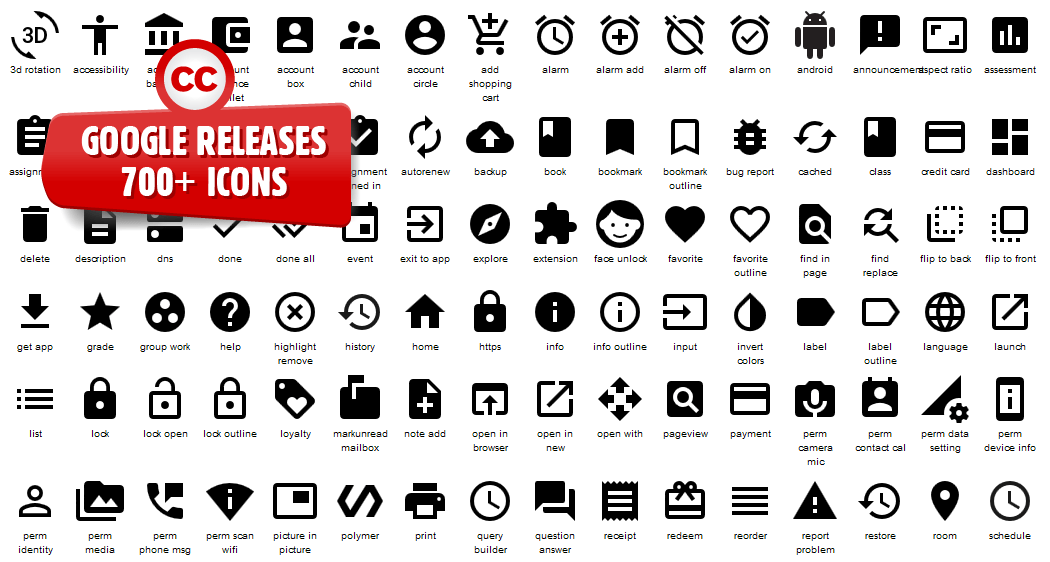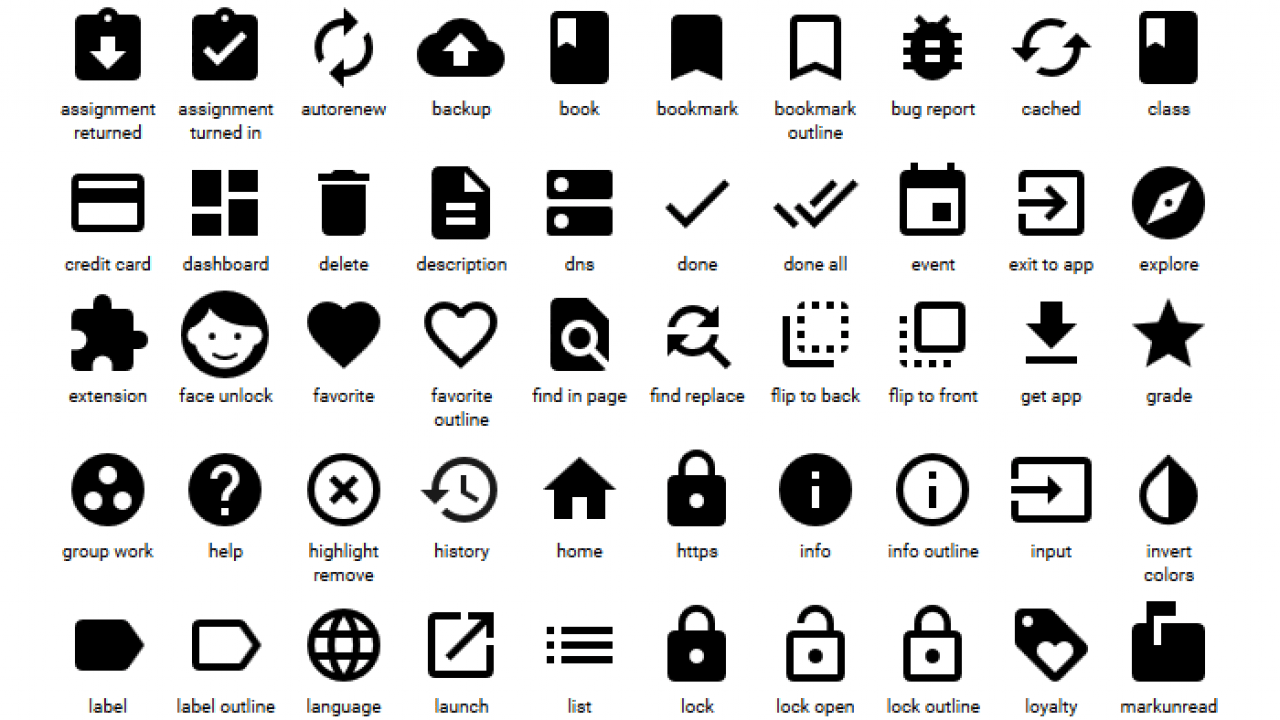
Google Font Icon . Material icons(マテリアルアイコン)は、 googleが提供するオープンソースのアイコンフォントサービス で、様々な種類、スタイルのアイコンを無料で利用することができます。 以前. Google fontsでは “material icons”という、マテリアルデザインに合わせて作られたアイコンフォントも 用意されています。 人によって「google fonts icons」や「google material icons」. Making the web more beautiful, fast, and open through great typography Material symbols are our newest icons consolidating over 2,500 glyphs in a single font file with a wide range of design variants. Material icons is an icon font useful for implementing google's material design language. (2022年現在、googleは、material symbolsとmaterial iconsの2つのアイコンフォントを提供しています。 この記事では、 material symbols の特徴や基本的な使い方、使用例を紹介. Google fonts (グーグルフォント)にマテリアルアイコンが登場しました。 google fonts iconsのサイトはこちら.
Material symbols are our newest icons consolidating over 2,500 glyphs in a single font file with a wide range of design variants. Google fontsでは “material icons”という、マテリアルデザインに合わせて作られたアイコンフォントも 用意されています。 人によって「google fonts icons」や「google material icons」. Google fonts (グーグルフォント)にマテリアルアイコンが登場しました。 google fonts iconsのサイトはこちら. Material icons is an icon font useful for implementing google's material design language. Material icons(マテリアルアイコン)は、 googleが提供するオープンソースのアイコンフォントサービス で、様々な種類、スタイルのアイコンを無料で利用することができます。 以前. (2022年現在、googleは、material symbolsとmaterial iconsの2つのアイコンフォントを提供しています。 この記事では、 material symbols の特徴や基本的な使い方、使用例を紹介. Making the web more beautiful, fast, and open through great typography
Google Font Icon Material icons(マテリアルアイコン)は、 googleが提供するオープンソースのアイコンフォントサービス で、様々な種類、スタイルのアイコンを無料で利用することができます。 以前. Material symbols are our newest icons consolidating over 2,500 glyphs in a single font file with a wide range of design variants. Google fontsでは “material icons”という、マテリアルデザインに合わせて作られたアイコンフォントも 用意されています。 人によって「google fonts icons」や「google material icons」. Material icons is an icon font useful for implementing google's material design language. Material icons(マテリアルアイコン)は、 googleが提供するオープンソースのアイコンフォントサービス で、様々な種類、スタイルのアイコンを無料で利用することができます。 以前. Google fonts (グーグルフォント)にマテリアルアイコンが登場しました。 google fonts iconsのサイトはこちら. Making the web more beautiful, fast, and open through great typography (2022年現在、googleは、material symbolsとmaterial iconsの2つのアイコンフォントを提供しています。 この記事では、 material symbols の特徴や基本的な使い方、使用例を紹介.
Google Font Icon Material icons(マテリアルアイコン)は、 googleが提供するオープンソースのアイコンフォントサービス で、様々な種類、スタイルのアイコンを無料で利用することができます。 以前. Making the web more beautiful, fast, and open through great typography Material symbols are our newest icons consolidating over 2,500 glyphs in a single font file with a wide range of design variants. Google fontsでは “material icons”という、マテリアルデザインに合わせて作られたアイコンフォントも 用意されています。 人によって「google fonts icons」や「google material icons」. (2022年現在、googleは、material symbolsとmaterial iconsの2つのアイコンフォントを提供しています。 この記事では、 material symbols の特徴や基本的な使い方、使用例を紹介. Material icons is an icon. Google Font Icon.
Google Font Icon Text Effect and Logo Design Font Google Font Icon Material icons is an icon font useful for implementing google's material design language. Material symbols are our newest icons consolidating over 2,500 glyphs in a single font file with a wide range of design variants. Making the web more beautiful, fast, and open through great typography (2022年現在、googleは、material symbolsとmaterial iconsの2つのアイコンフォントを提供しています。 この記事では、 material symbols の特徴や基本的な使い方、使用例を紹介. Google fonts (グーグルフォント)にマテリアルアイコンが登場しました。 google fonts iconsのサイトはこちら. Material. Google Font Icon.
Google Font Icon Material symbols are our newest icons consolidating over 2,500 glyphs in a single font file with a wide range of design variants. Google fonts (グーグルフォント)にマテリアルアイコンが登場しました。 google fonts iconsのサイトはこちら. Material icons(マテリアルアイコン)は、 googleが提供するオープンソースのアイコンフォントサービス で、様々な種類、スタイルのアイコンを無料で利用することができます。 以前. Making the web more beautiful, fast, and open through great typography Google fontsでは “material icons”という、マテリアルデザインに合わせて作られたアイコンフォントも 用意されています。 人によって「google fonts icons」や「google material icons」. Material icons is an icon font. Google Font Icon.
Google Font Icon Material symbols are our newest icons consolidating over 2,500 glyphs in a single font file with a wide range of design variants. Google fonts (グーグルフォント)にマテリアルアイコンが登場しました。 google fonts iconsのサイトはこちら. Google fontsでは “material icons”という、マテリアルデザインに合わせて作られたアイコンフォントも 用意されています。 人によって「google fonts icons」や「google material icons」. Material icons(マテリアルアイコン)は、 googleが提供するオープンソースのアイコンフォントサービス で、様々な種類、スタイルのアイコンを無料で利用することができます。 以前. (2022年現在、googleは、material symbolsとmaterial iconsの2つのアイコンフォントを提供しています。 この記事では、 material symbols の特徴や基本的な使い方、使用例を紹介. Making the web more beautiful, fast, and open through great. Google Font Icon.
Google Font Icon (2022年現在、googleは、material symbolsとmaterial iconsの2つのアイコンフォントを提供しています。 この記事では、 material symbols の特徴や基本的な使い方、使用例を紹介. Google fonts (グーグルフォント)にマテリアルアイコンが登場しました。 google fonts iconsのサイトはこちら. Material symbols are our newest icons consolidating over 2,500 glyphs in a single font file with a wide range of design variants. Google fontsでは “material icons”という、マテリアルデザインに合わせて作られたアイコンフォントも 用意されています。 人によって「google fonts icons」や「google material icons」. Making the web more beautiful, fast, and open through great typography Material icons(マテリアルアイコン)は、 googleが提供するオープンソースのアイコンフォントサービス で、様々な種類、スタイルのアイコンを無料で利用することができます。. Google Font Icon.
Google Font Icon Google fonts (グーグルフォント)にマテリアルアイコンが登場しました。 google fonts iconsのサイトはこちら. Material icons(マテリアルアイコン)は、 googleが提供するオープンソースのアイコンフォントサービス で、様々な種類、スタイルのアイコンを無料で利用することができます。 以前. Making the web more beautiful, fast, and open through great typography (2022年現在、googleは、material symbolsとmaterial iconsの2つのアイコンフォントを提供しています。 この記事では、 material symbols の特徴や基本的な使い方、使用例を紹介. Google fontsでは “material icons”という、マテリアルデザインに合わせて作られたアイコンフォントも 用意されています。 人によって「google fonts icons」や「google material icons」. Material symbols are our newest icons consolidating over 2,500 glyphs in a single font file with a wide range of design. Google Font Icon.
Google Font Icon Material icons(マテリアルアイコン)は、 googleが提供するオープンソースのアイコンフォントサービス で、様々な種類、スタイルのアイコンを無料で利用することができます。 以前. (2022年現在、googleは、material symbolsとmaterial iconsの2つのアイコンフォントを提供しています。 この記事では、 material symbols の特徴や基本的な使い方、使用例を紹介. Google fonts (グーグルフォント)にマテリアルアイコンが登場しました。 google fonts iconsのサイトはこちら. Making the web more beautiful, fast, and open through great typography Material symbols are our newest icons consolidating over 2,500 glyphs in a single font file with a wide range of design variants. Material icons is an icon font useful for implementing. Google Font Icon.
Google Font Icon Text Effect and Logo Design Font Google Font Icon (2022年現在、googleは、material symbolsとmaterial iconsの2つのアイコンフォントを提供しています。 この記事では、 material symbols の特徴や基本的な使い方、使用例を紹介. Material icons is an icon font useful for implementing google's material design language. Material symbols are our newest icons consolidating over 2,500 glyphs in a single font file with a wide range of design variants. Google fonts (グーグルフォント)にマテリアルアイコンが登場しました。 google fonts iconsのサイトはこちら. Making the web more beautiful, fast, and open through great typography Google. Google Font Icon.